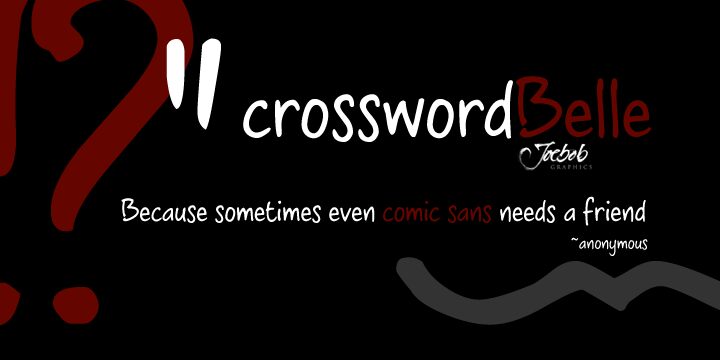
Crossword Belle od JJW van der Ham z JOEBOB graphics to darmowy, zaokrąglony font odręczny o luźnym, przyjaznym rytmie. Litery opierają się na szerokich pociągnięciach i miękkich krzywiznach, z dynamicznymi łączeniami i otwartymi kształtami, co nadaje całości swobodny charakter, przypominający notatkę na papierze, zamiast wygładzonej kaligrafii.
Naturalnie pasuje do opakowań, menu kawiarnianych, kartek okolicznościowych, tytułów w albumach i zabawnego brandingu, gdzie darmowy font może utrzymać ciepły i nieformalny ton. Użyj go w krótkich nagłówkach, na okładkach lub w etykietach, gdy szukasz napisu, który wygląda na ręcznie rysowany i sprawia wrażenie spontanicznego, ale nieprzesadzonego.